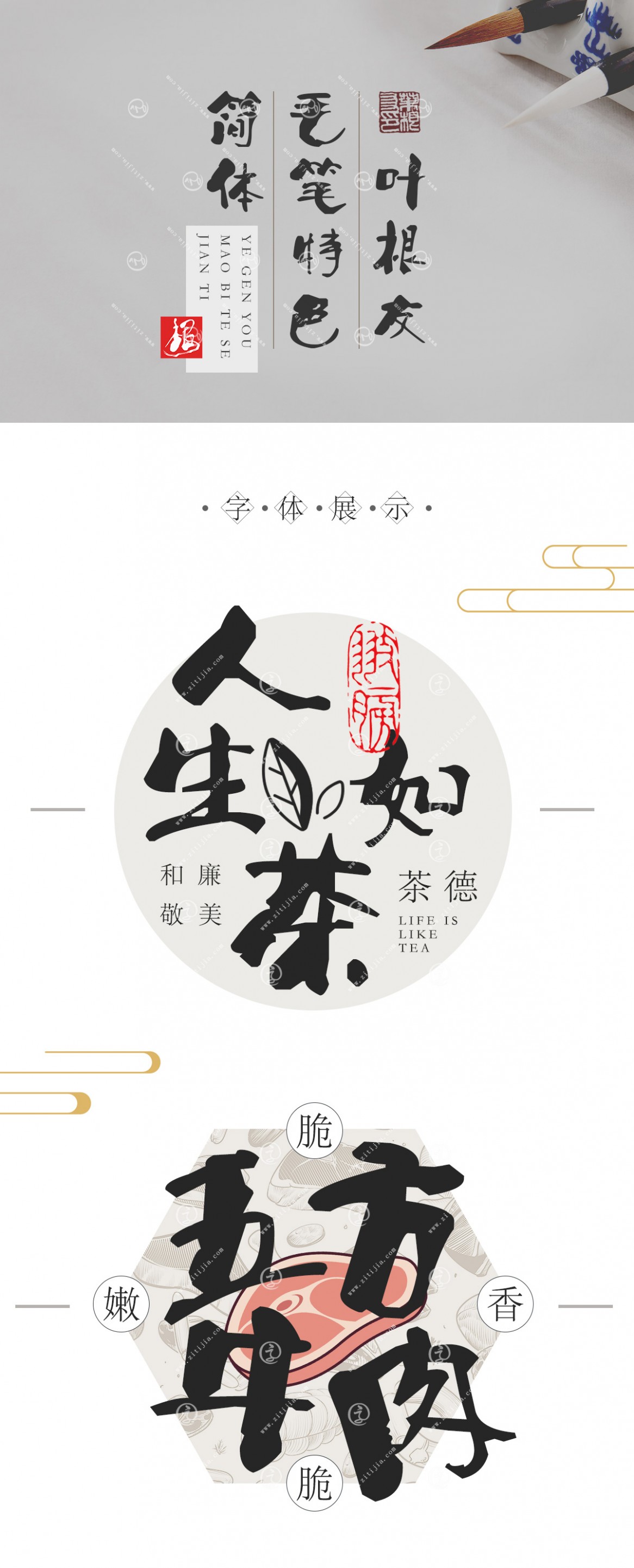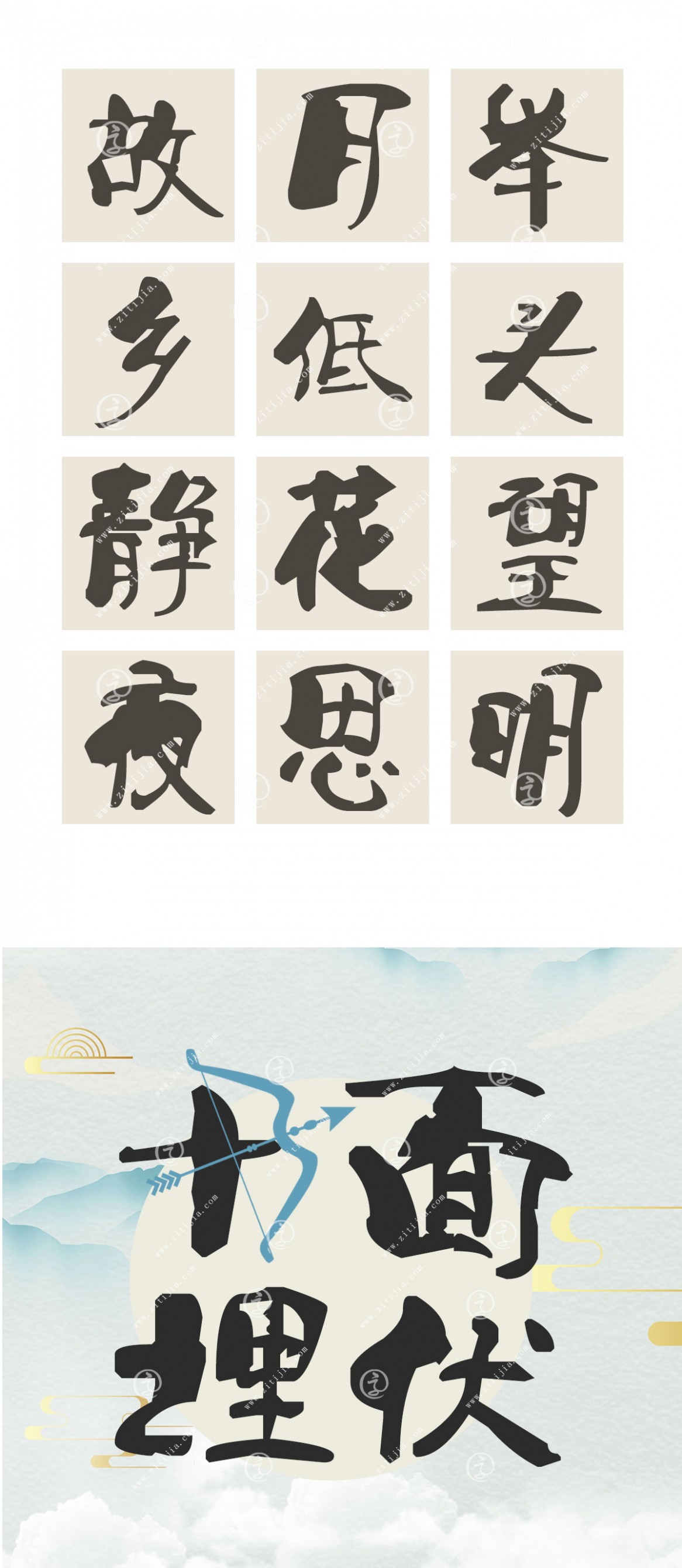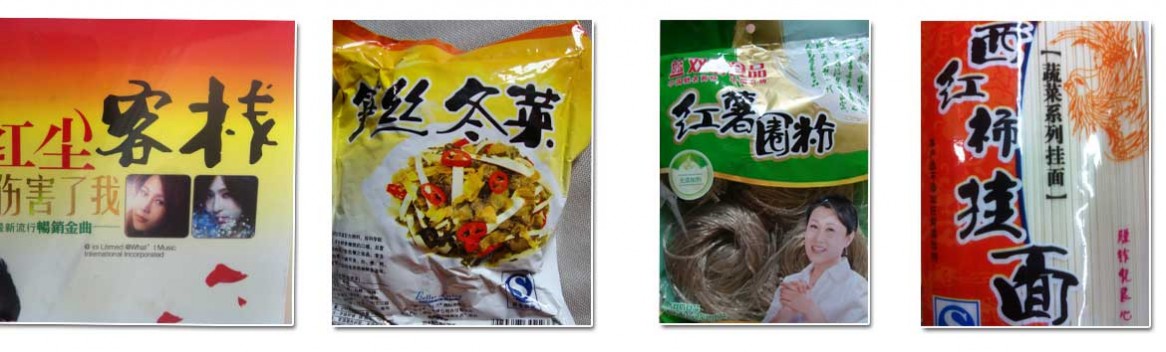
葉根友毛筆特色簡體
字體作者:葉根友
創(chuàng)作年代:2007年
字體字?jǐn)?shù):6763個中文漢字以及其他英文字母和阿拉伯?dāng)?shù)字
字體介紹
葉根友毛筆特色簡體被列為葉根友字體系列最受歡迎的字體之一。
一款具有獨特氣質(zhì)的毛筆書法字體,渾厚自然的筆畫,使書法與現(xiàn)代審美相結(jié)合,葉根友毛筆特色簡體字體是一款有隸書風(fēng)格的手寫字體。
簡潔明了,筆畫有粗有細(xì),有正有奇,字型獨特創(chuàng)意的一款字體,該字體特色明顯,打破傳統(tǒng)毛筆書法寫法,自創(chuàng)一派,用筆大膽而干練,在粗與細(xì)的對比中,體現(xiàn)了中國漢字千變?nèi)f化的特征,只要有想象,只要有創(chuàng)意,書法字體也可以完全被創(chuàng)意包圍
創(chuàng)作記事
2007年7月,初創(chuàng)該字體字稿
2007年7月,發(fā)行葉根友毛筆特色簡體1.0版本